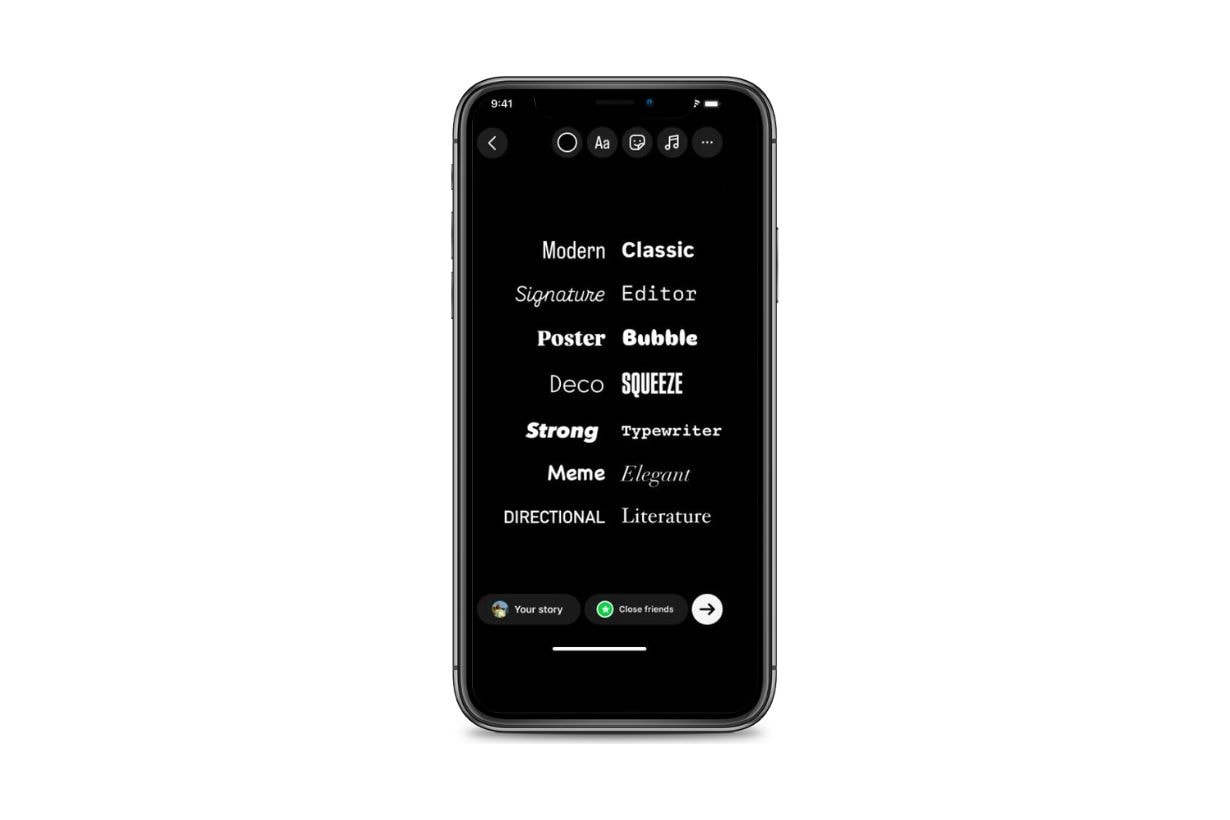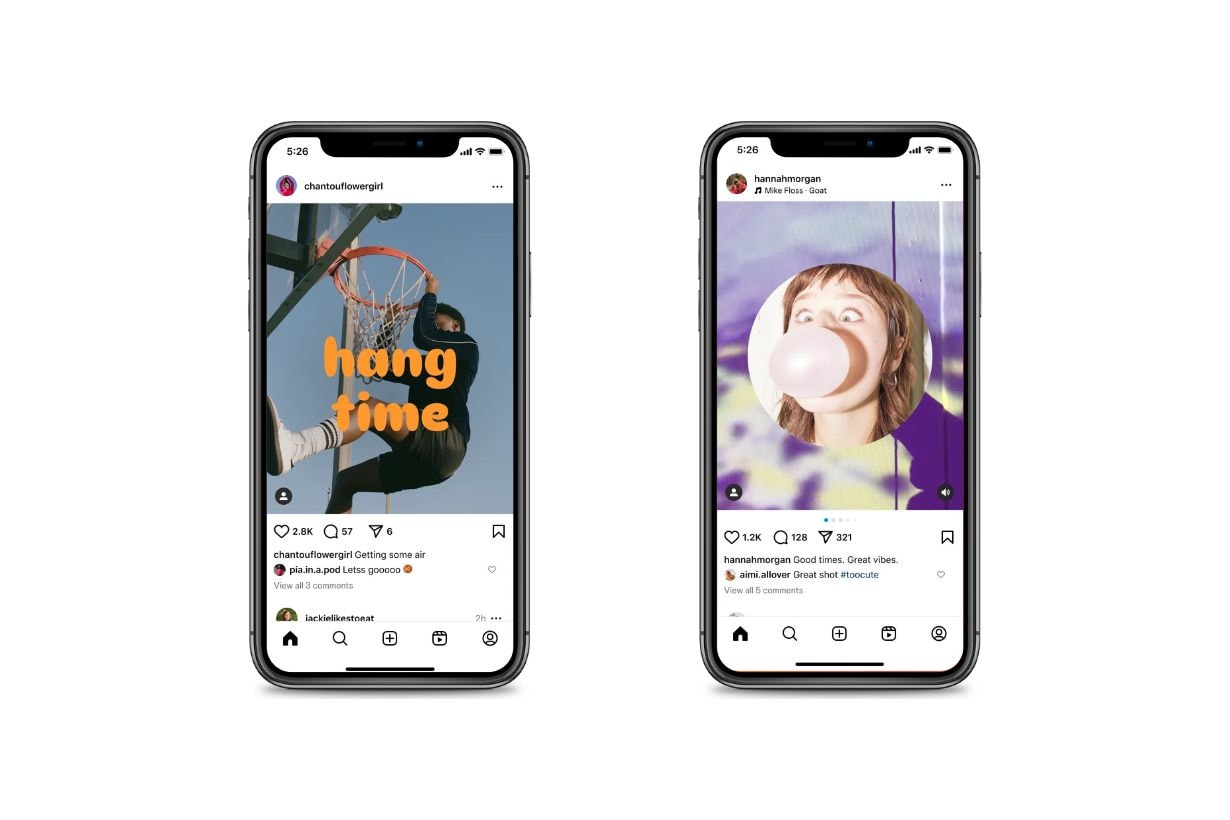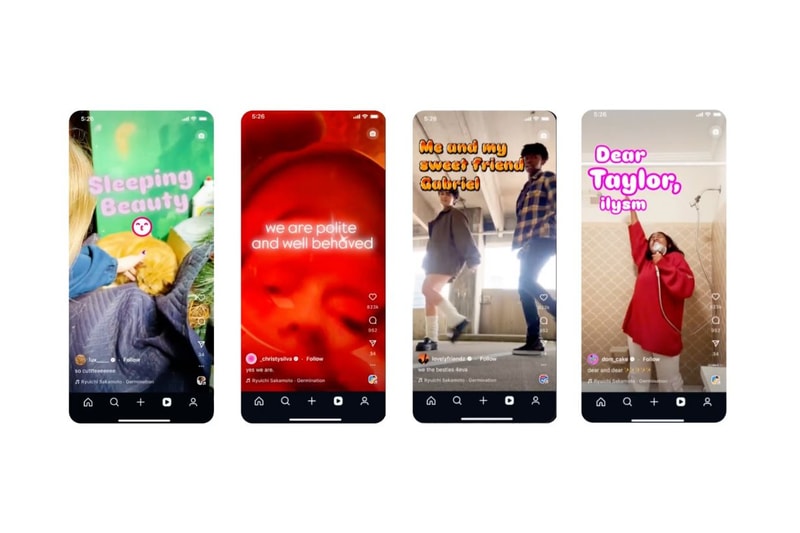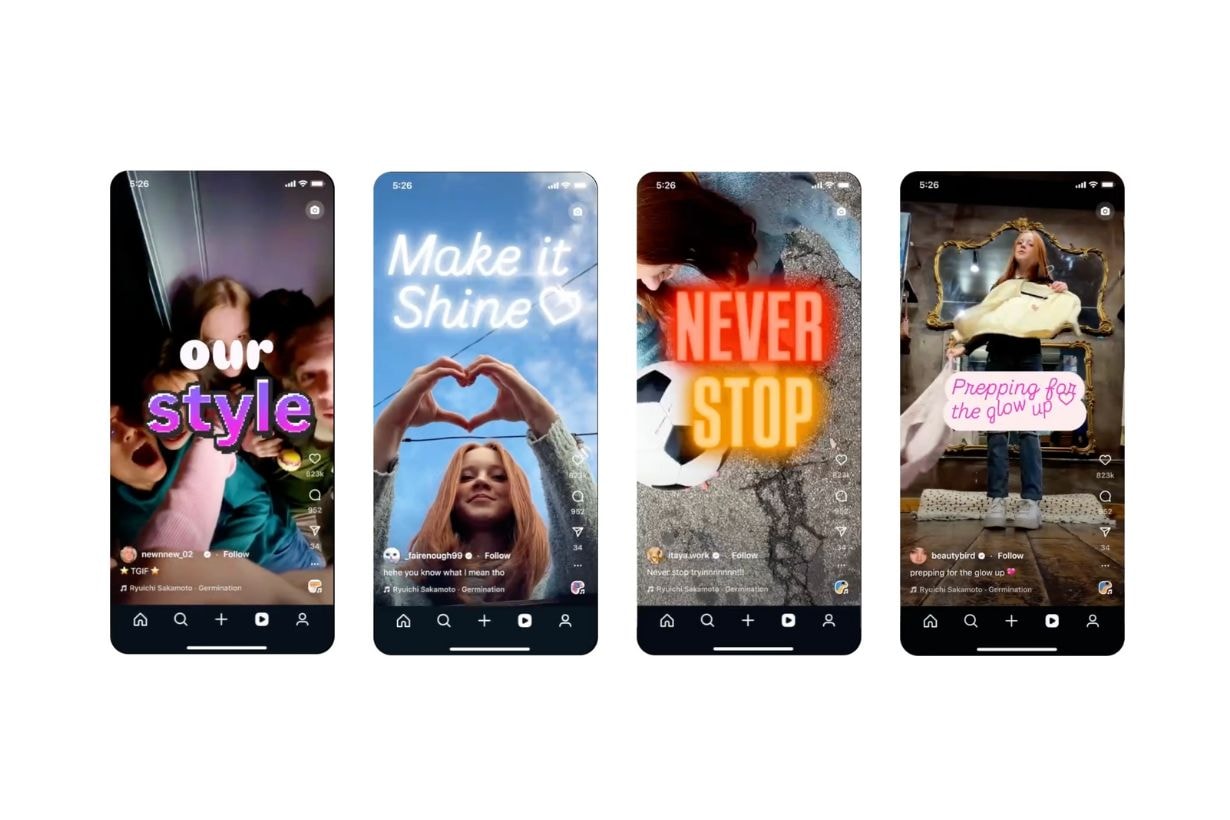
不只能發 20 張圖片:Instagram 限時動態新字體+動畫你玩過了嗎!
試試看你的 Instagram 有沒有新功能!
當社群已經成為我們生活的一部分,相信不少人的日常也離不開 Instagram,從分享有趣日常、與朋友聯繫到開啟新的商業模式,Instagram 在成為 Meta 的一份子之後接連帶來了不少革新,許多用戶樂於迎接改變,也有一些使用者更偏好過往簡約的版面,不論你是以上何者,也擋不住 Instagram 推出新功能的速度,其中不久前剛剛推出的 Stories 字體各位也玩過了嗎?
近期 Instagram 剛剛公開將下架非官方濾鏡的消息,就引起不少討論,雖然 Meta Spark 終止營運將讓不少過去愛用的濾鏡消失,但似乎也意味著官方將推出更多新功能讓大家能在影片上玩出不同花樣,而近期 Instagram 確實也帶來了不少創意工具,除了貼文的照片數量能增加到 20 則之外,連限時動態、Reels 也帶來了新字體與動畫!
不久前 Instagram 官方公佈了能讓使用者自由創作的新功能,其中就包括 6 種不同風格的字體「Signature」、「Bubble」、「Poster」、「Deco」、「Editor」、「Squeeze」,設計也跟上了復古潮流並搭配新的動畫效果呈現,使用者只要在輸入文字後於下方選擇並預覽即可,同時 Instagram 也讓你可以將文字加入在貼文的照片當中,並且可以搭配疊加不同圖片來玩出新花樣,讓你更自由的根據每日心情來發文。